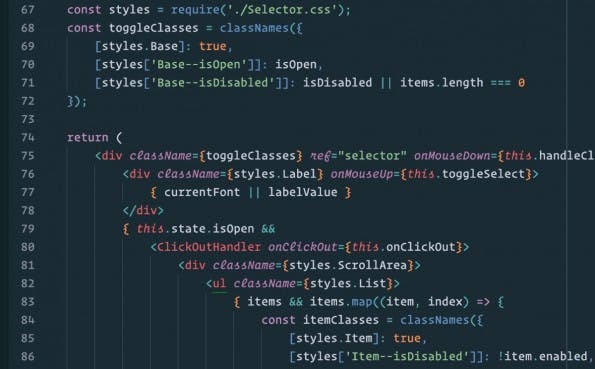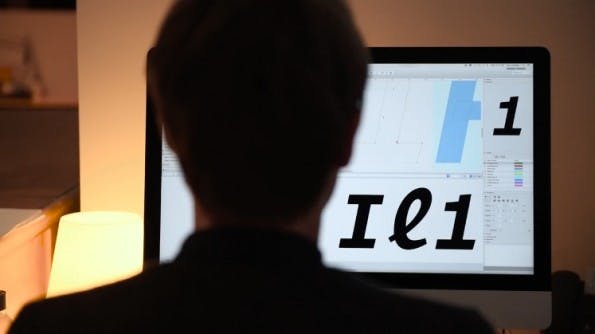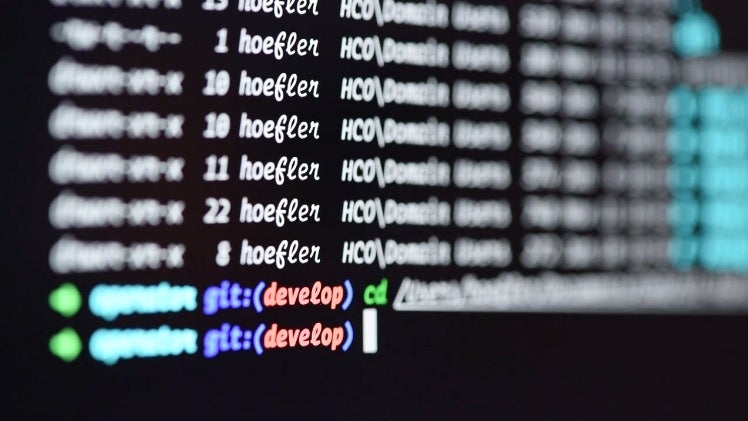
Der Font „Operator Mono“ will euch das Coden erleichtern
„Operator Mono“ von Hoefler & Co. (Screenshot: typography.com)
Die Schrift Operator Mono richtet sich an Entwickler und Designer
„Operator Mono“ von Hoefler & Co. (Screenshot: typography.com)
Die Firma „Hoefler & Co.“ gehört zu den einflussreichen Schriftenherstellern der letzten Jahre. Mit „Operator Mono“ hat das in New York ansässige Unternehmen jetzt einen Font vorgestellt, der vor allem Designern und Programmieren die Arbeit deutlich erleichtern soll.
Seinen Ursprung hat der neue Font im Wunsch der Designer, eine Monospace-Schriftart zu entwickeln, die sich trotzdem nicht sklavisch an fest vorgegebene Zeichenbreiten hält, sondern diese, wo gewünscht, auch durch proportionale Elemente ergänzt. Auf diese Weise ist die Schriftfamilie „Operator“ entstanden.
Operator Mono: Lupenreiner Monospace-Font mit kursiven Elementen
In einem zweiten Schritt, so beschreiben es die Macher in einem Blogeintrag, sei ihnen die Idee gekommen, die Freiheiten ihrer neuen Schrift speziell in den Dienst besserer Lesbarkeit beim Programmieren zu stellen. Hierbei allerdings nicht durch variable Zeichenbreiten – „Operator Mono“ ist anders als sein Cousin „Operator“ ein lupenreiner Monospace-Font – sondern durch die gestalterische Orientierung an Schreibschriften und ihrem Einsatz beispielsweise von Serifen. Auf diese Weise soll „Operator Mono“ beispielsweise die Unterscheidung zwischen „I“, „l“ und „1“ deutlich erleichtern oder lange Code-Reihen, die erst durch farbliche Hervorhebungen des jeweiligen Editors wirklich lesbar werden, auch in schwarz-weiß gut erkennbar machen.
In der folgenden Grafik veranschaulichen die Designer, wie die Arbeit mit „Operator Mono“ im Atom-Editor aussehen könnte:
„Die charakteristischen Kursivbuchstaben der Schriftfamilie machen es leichter, die Namen von Attributen zu erkennen.“
Der Font „Operator Mono“ in der Umgebung des Atom-Editors. (Grafik: Hoefler & Co.)
Auch die Frage, ob es eine Schrift wirklich lesbarer macht, sie mit kursiven Elementen zu versehen, dürften viele Anwender anders beantworten als Hoefler & Co. In den Kommentaren bei Engadget, das die Schrift gestern vorgestellt hat, wird daher schon gemutmaßt, ob die Designer der Schrift überhaupt selbst schon einmal programmiert oder nur geraten haben, was den Umgang mit Code möglicherweise erleichtern könnte. Bildet euch am besten euer eigenes Urteil anhand der Übersichtsseite zu den Operator-Fonts.
Coding Fonts: Alternativen zu Operator Mono
Trotzdem sei erwähnt, dass es neben „Operator Mono“ diverse andere Schriften gibt, die ebenfalls zum Ziel haben, Code leichter les- und bearbeitbar zu machen: Da wäre zum Beispiel der deutlich günstigere Input-Font, den wir euch an anderer Stelle vorgestellt haben. Mit „Source Code Pro“ und „Hack“ gibt es sogar zwei kostenfreie Fonts, die für Coding-Umgebungen optimiert sind. Und auch in unserem Artikel „Schicker Code: Die besten Fonts zum Programmieren“ finden sich gute Alternativen.
Das Kursivschrift die Lesbarkeit von Code erhöht, kann man bezweifeln. Wer eine echten Programmierer-Font braucht, sollte sich die frei Typo HACK mal ansehen.
Meine Wahl wäre diese nicht. Wenn ich erstmal drüber nachdenken muss welches Zeichen (@) mir dargestellt wird, hat die Schrift eigentlich schon versagt.
Ein Entwickler wird die 200 EUR lieber in eine neue mechanische Tastatur investieren, die seine Arbeit produktiver beeinflusst als kursive Fonts. Zumal ein typischer Hoefler-Designer wahrscheinlich an einem Bildschirm mit 27 Zoll und mehr sitzt und höhere Schriftgrößen nutzt, während ein typischer Entwickler maximal über einen 24 Zoll Bildschirm verfügt und selbst dort kleinere Schriftgrößen bevorzugt, damit mehr Code auf die Fläche passt.